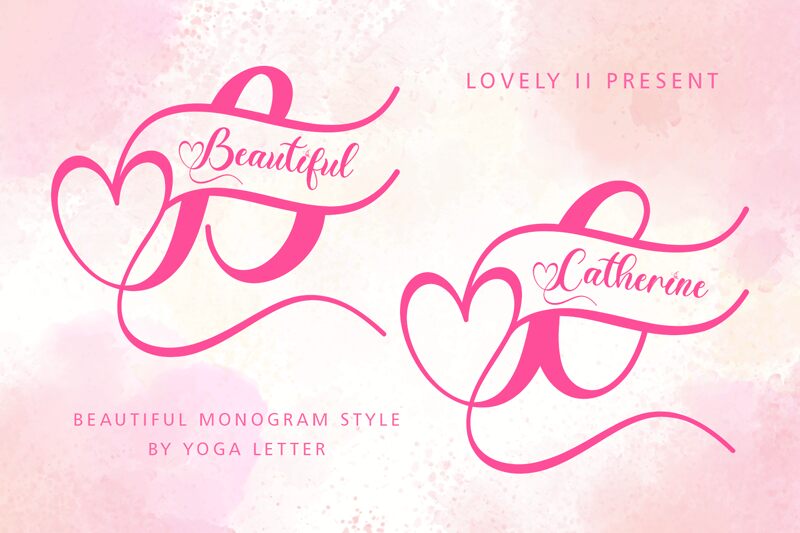
Beautiful Catherine Monogram De
Beautiful Catherine Monogram, créée par Yoga Letter, est une police script gratuite idéale pour la Saint-Valentin. Son style calligraphique fluide, agrémenté d'une ouverture en forme de cœur et d'un soulignement élégant, confère à vos créations un aspect monogramme personnalisé. Les lettres liées conservent un rythme doux et formel, tandis que les courbes généreuses sont parfaitement adaptées aux compositions romantiques.
Beautiful Catherine Monogram est une police gratuite parfaite pour les faire-part de mariage, les cartes de Saint-Valentin, les logos de boutiques, les étiquettes cadeaux et les initiales monogrammées, là où un style signature décoratif fait toute la différence. Ses traits liés et ses détails en forme de cœur la rendent idéale pour les noms courts, les logos et les textes d'accentuation qui nécessitent une touche manuscrite sans pour autant paraître trop informelle.